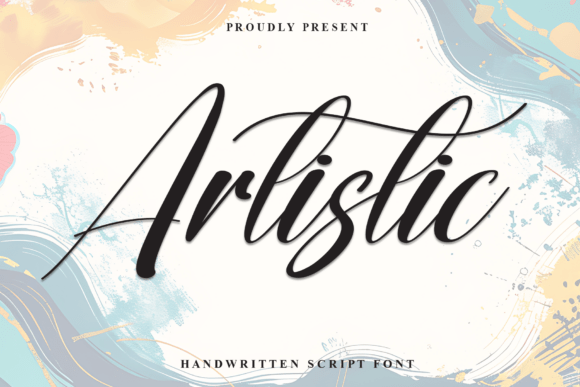
Artistic
หากคุณกำลังมองหาเนื้อหาคุณภาพสูงเช่น Artistic แพ็คเกจพรีเมียมนี้เป็นตัวเลือกที่ยอดเยี่ยมสำหรับโปรเจ็กต์สร้างสรรค์ของคุณ
ไม่ว่าคุณจะสร้างผลิตภัณฑ์ POD (Print on Demand) คำเชิญงานแต่งงาน หรือกราฟิกโซเชียลมีเดีย Artistic ก็เหมาะสมอย่างยิ่ง